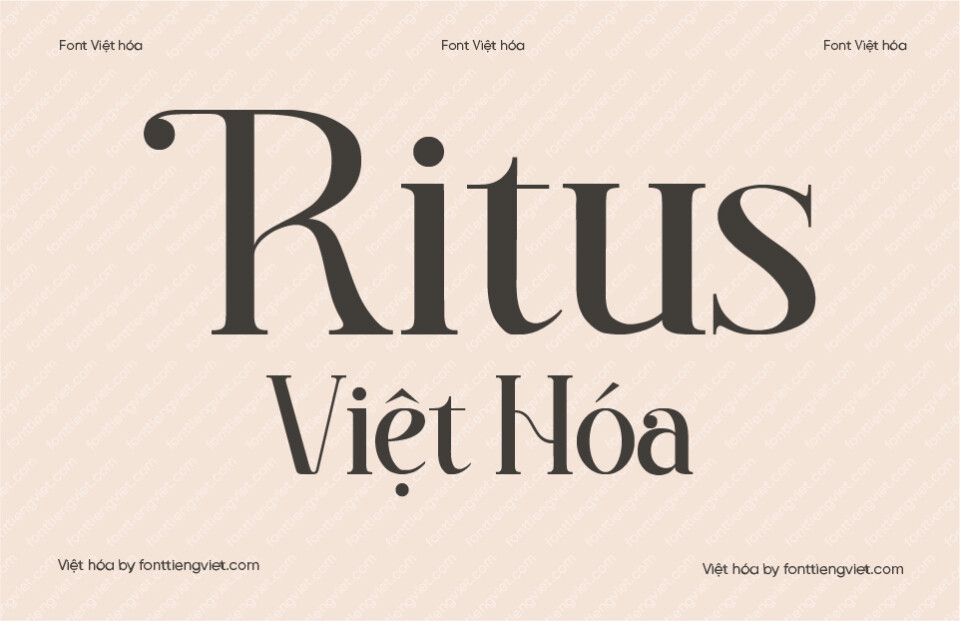
Font Việt hóa 1FTV VIP Ritus
Giới thiệu về bộ Font Việt hóa 1FTV VIP Ritus
Trong thế giới thiết kế đồ họa hiện đại, việc lựa chọn một Font Miễn Phí phù hợp đóng vai trò then chốt giúp truyền tải thông điệp một cách ấn tượng nhất. Font Việt hóa 1FTV VIP Ritus nổi lên như một hiện tượng trong cộng đồng designer Việt Nam nhờ phong cách độc đáo, pha trộn giữa nét cổ điển và hơi thở đương đại. Đây là bộ phông chữ được tinh chỉnh kỹ lưỡng về dấu tiếng Việt, đảm bảo không xảy ra lỗi hiển thị khi soạn thảo văn bản. Với đường nét thanh thoát nhưng không kém phần mạnh mẽ, bộ font này giúp các tác phẩm từ banner, poster đến bìa sách trở nên chuyên nghiệp và thu hút ánh nhìn hơn bao giờ hết.
Đặc điểm nổi bật của Font Việt hóa 1FTV VIP Ritus
Bộ Font Việt hóa 1FTV VIP Ritus sở hữu những đặc tính kỹ thuật vượt trội mà ít bộ font miễn phí nào có được. Đầu tiên là hệ thống glyphs đa dạng, cho phép người dùng tùy biến linh hoạt trong các dự án sáng tạo. Các ký tự được thiết kế với tỷ lệ vàng, tạo ra sự cân đối hoàn hảo khi sắp đặt bố cục chữ. Đặc biệt, font chữ này hỗ trợ đầy đủ các bảng mã phổ biến, giúp các bạn học sinh và giáo viên dễ dàng ứng dụng vào việc làm bài thuyết trình hay thiết kế giáo án điện tử mà không lo ngại về vấn đề tương thích hệ điều hành.
Ứng dụng thực tế của Font Việt hóa 1FTV VIP Ritus trong đời sống
Không chỉ giới hạn trong lĩnh vực quảng cáo, Font Việt hóa 1FTV VIP Ritus còn được ứng dụng rộng rãi trong nhiều bối cảnh khác nhau. Trong môi trường học đường, các bạn học sinh có thể sử dụng font này để tạo ra những tiêu đề báo tường sinh động hoặc làm nổi bật các ý chính trong tập san lớp. Đối với các nhà thiết kế chuyên nghiệp, đây là lựa chọn hàng đầu cho các dự án nhận diện thương hiệu đòi hỏi sự sang trọng và tinh tế. Sự kết hợp giữa nét chữ nghệ thuật và khả năng đọc hiểu tốt giúp font chữ này giữ được giá trị thẩm mỹ cao trong mọi kích thước hiển thị.
Lợi ích khi sử dụng Font Việt hóa 1FTV VIP Ritus
Sử dụng Font Việt hóa 1FTV VIP Ritus giúp tiết kiệm đáng kể thời gian chỉnh sửa dấu câu thủ công. Nhờ quy trình Việt hóa chuyên nghiệp, mọi ký tự như ă, â, đ hay các dấu thanh đều được đặt đúng vị trí, đảm bảo tính thẩm mỹ cho văn bản. Bên cạnh đó, việc sử dụng font chữ đã được tối ưu giúp dung lượng file thiết kế nhẹ hơn, hỗ trợ quá trình xuất bản và in ấn diễn ra mượt mà. Đây thực sự là công cụ đắc lực cho những ai đang tìm kiếm sự phá cách nhưng vẫn giữ được nét thuần Việt trong từng câu chữ.
Kết luận về bộ phông chữ đặc biệt này